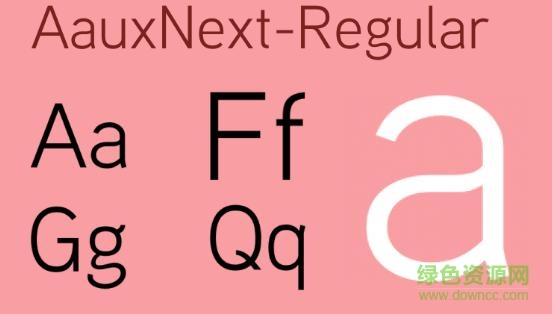
aauxnext 字體是一款特點(diǎn)鮮明的無襯線字體,棱角分明,風(fēng)格簡約,極富時(shí)代氣息,適合用于各類視覺設(shè)計(jì),有需要者歡迎免費(fèi)下載!
通常來說,食品、女性用品、兒童用品,以及一些消費(fèi)群體為年輕化的產(chǎn)品,或者產(chǎn)品特質(zhì)需要給人一種親切感受的,在字體的選擇上,更適合一些有弧線,沒有襯線,并且字形相對柔和一些的字體。